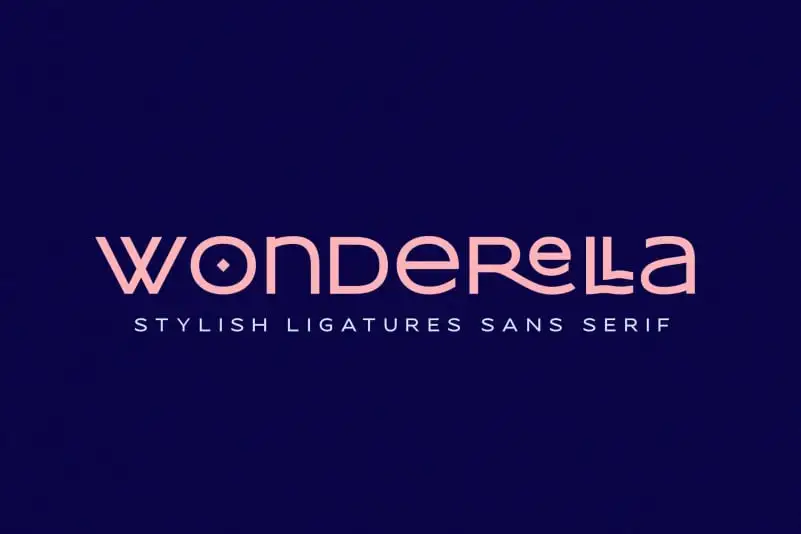
Wonderella Display Font – Download Grátis
Wonderella Display Font é uma elegante tipografia sans serif para projetos luxuosos. Seu design cuidadosamente refinado representa glamour e majestade através de letras com alto contraste, oferecendo um toque delicado e sofisticado. Esta fonte foi criada pelo talentoso designer Almarkhatype Studio. Perfeita tanto para Instagram stories quanto para scripts artesanais em projetos DIY, ela transforma qualquer ideia criativa num verdadeiro trabalho de arte. Seja você uma pessoa que busca inspiração nas redes sociais ou um entusiasta do design manual e artesanal, a Wonderella Display Font tem o potencial de revolucionar suas criações. Seu estilo casual mas amigável torna-a perfeita para quem gosta de adicionar personalidade sem comprometer a elegância, permitindo que sua arte seja ainda mais única e memorável.